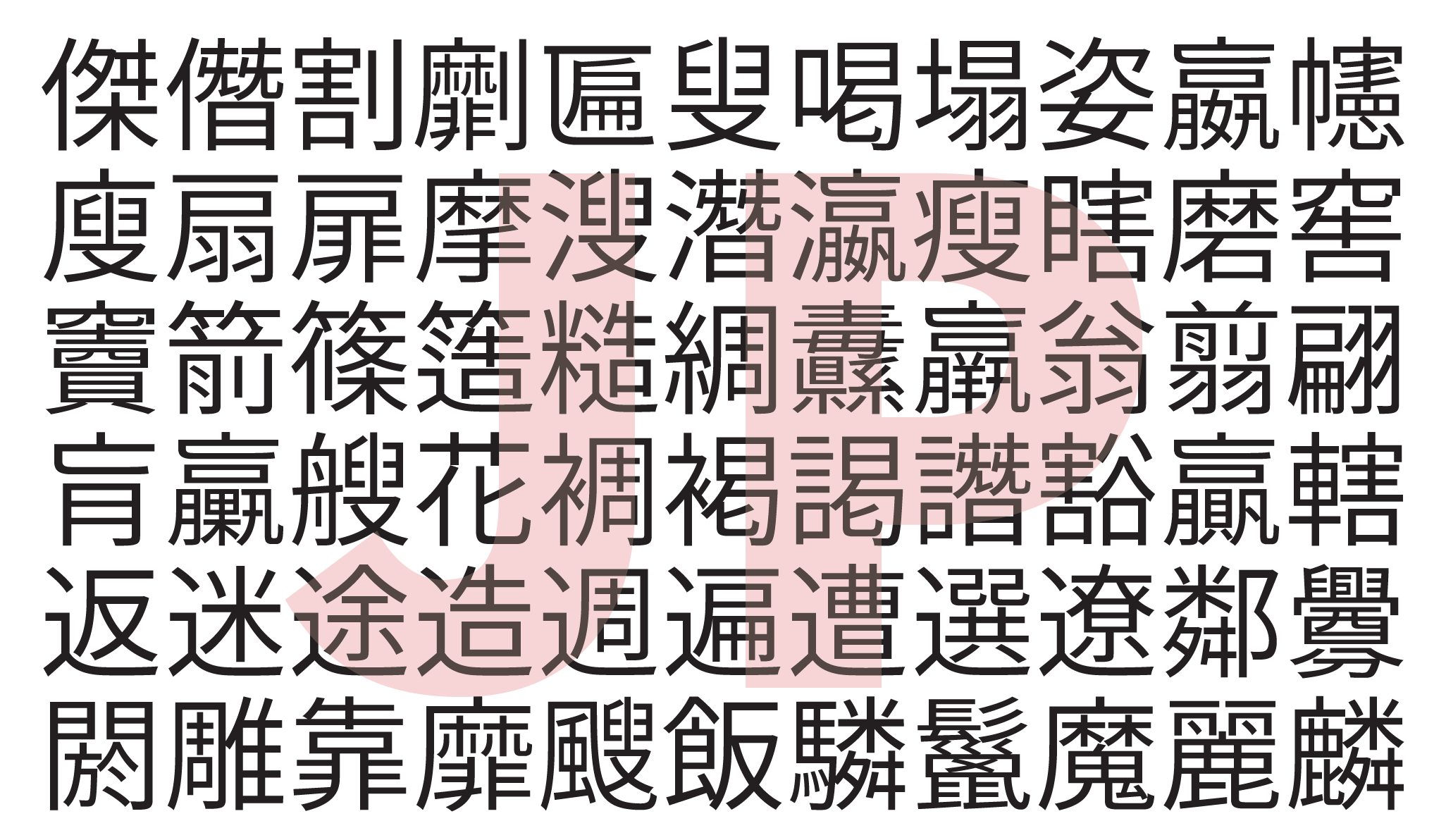
Ресурс-пак Modern Font Pack заменяет стандартный шрифт Майнкрафт на гладкий современный шрифт Noto Sans. Три варианта сглаживания (Basic, HD, Supreme) для разных разрешений, поддержка эмодзи и нестандартных символов. Совместимость с Java Edition 1.5 - последними версиями и Bedrock Edition.
Надоел толстый и грубый шрифт в Майнкрафт по умолчанию? Даже включение Force Unicode Font не спасает на больших экранах. Modern Font Pack решает эту проблему - он заменяет иконки и буквы на красивые, гладкие шрифты из семейства Noto Sans от Google. Это не мод, а обычный ресурс-пак (текстурпак), который можно установить в любом лаунчере.
Если ты ищешь производный проект, который решает некоторые проблемы с жирным шрифтом и свечением, посмотри Modern Font Pack - Caxton Edition.
Варианты сглаживания и региональные версии
У Modern Font Pack есть три степени сглаживания:
• Basic - простое сглаживание для низких разрешений (например, старые мониторы) или GUI Scale 2. Не рекомендуется для больших экранов.
• HD - нормальное сглаживание для средних и высоких разрешений (вплоть до Full HD) при GUI Scale 3 и выше.
• Supreme - максимальное сглаживание для QHD (2560×1440), 4K и выше. Работает только на Minecraft 1.13 и новее, так как использует TTF-шрифты.
Каждая версия доступна в пяти региональных вариантах иероглифов (CJK):
• J - японский стандарт
• K - корейский стандарт
• C - китайский стандарт (упрощённый)
• T - тайваньский стандарт
• H - гонконгский стандарт
Если ты не используешь иероглифы, можешь выбирать любую - разница только в написании некоторых символов.
Эмодзи и модные символы
Ресурс-пак поддерживает эмодзи (начиная с версии 1.16) и нестандартные символы (fancy text). Просто скопируй их из любого онлайн-генератора и вставь в игру - команды /tellraw не нужны. Правда, из-за ограничений Майнкрафта некоторые составные эмодзи (вроде 👨‍👩‍👧) могут отображаться некорректно. Также, чтобы после окрашивания игры эмодзи не глючили, они сделаны одноцветными - цветные версии не планируются.
2. В чём разница между Basic, HD и Supreme? Из-за разного разрешения экрана и рендеринга шрифтов в Майнкрафт один и тот же ресурс-пак выглядит по-разному. Basic подходит для низких разрешений и GUI Scale 2, HD - для средних и высоких (GUI Scale 3+), Supreme - для 4K и GUI Scale 6+.
3. Почему Supreme только для 1.13+? Supreme использует TTF-шрифты, которые Майнкрафт начал поддерживать только с 1.13. Делать такие шрифты в формате изображений было бы слишком тяжело.
4. Какие отличия между CJK-вариантами? Разное написание некоторых иероглифов в зависимости от страны. Например, иероглиф "返" пишется по-разному в Японии, Корее, Китае, Тайване и Гонконге.
Дальнейшее развитие - добавление символов из дополнительной многоязычной плоскости Unicode (SMP) для версий 1.16+.